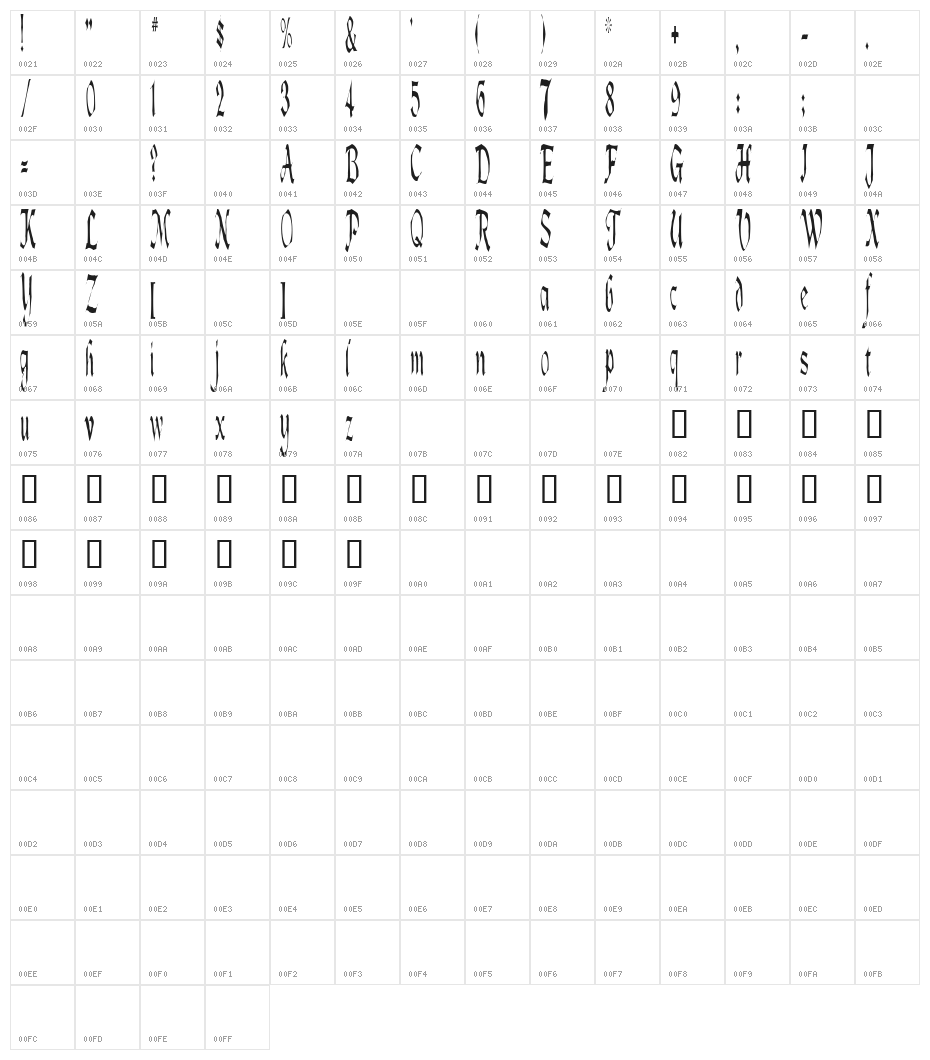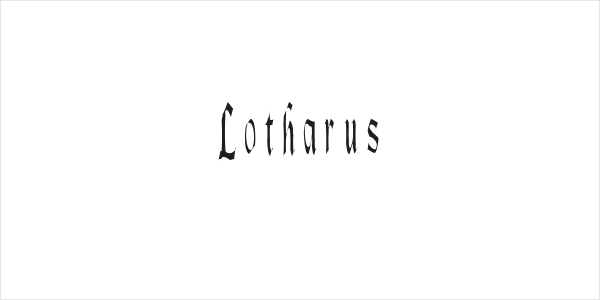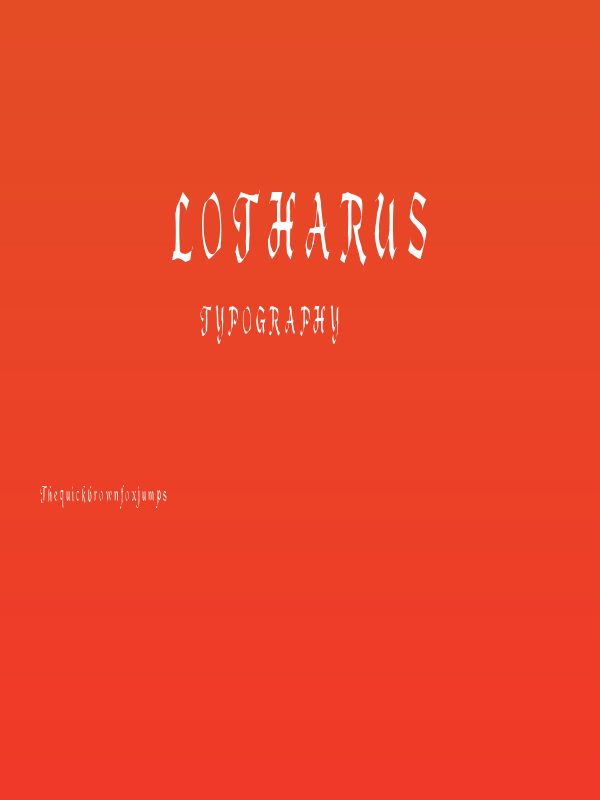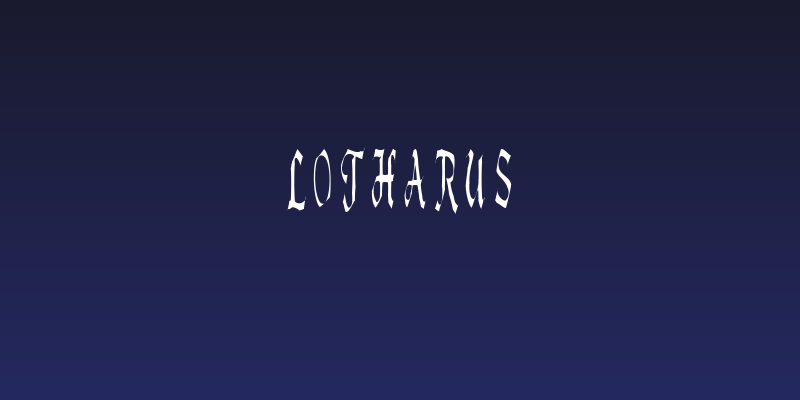
Lotharus Font
| الفئات | Script |
| العرض | Condensed |
| النمط العام | Vintage |
| حالة الاستخدام | Logos, Headlines, Decorative text |
| مشاريع مقترحة | Ideal for historical documents, vintage posters, book covers, and branding that requires a medieval or gothic touch. |